Geometrische Typographie – ein Schrift-Missverständnis
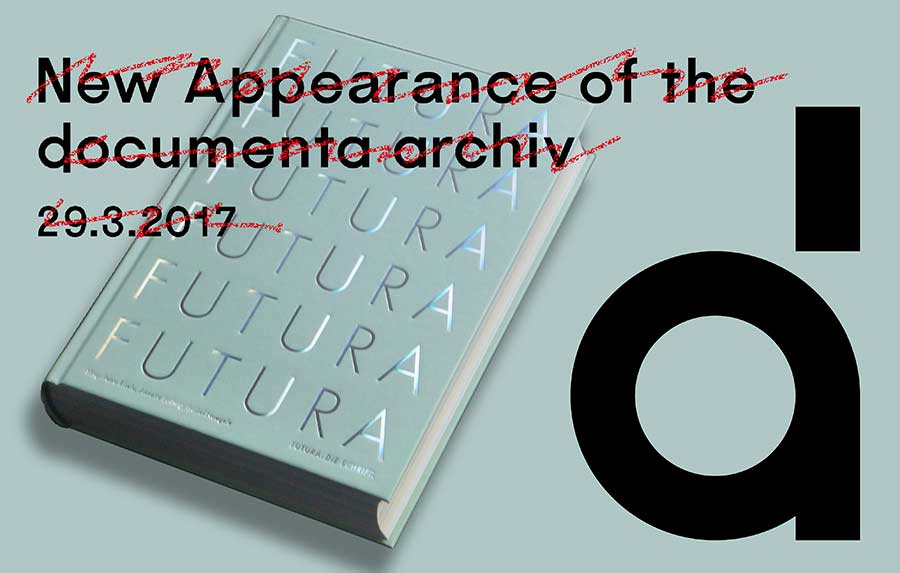
Die Vorstellung eines neuen Buches, das sich ausschließlich der Schrift „Futura“ widmet, hatte Doc Baumann für den heutigen Termin schon länger geplant. Zufällig präsentierte das Kasseler documenta-Archiv drei Tage zuvor sein neues Logo und eine eigens entworfene Schrift. Ein passender Anlass, um auf gelungene und misslungene Beispiele geometrisch konstruierter Schriften einzugehen.
Wahrscheinlich versucht fast jeder Grafiker im Laufe seiner Ausbildung irgendwann einmal, eine eigene Schrift zu entwickeln. Da er oder sie bis dahin zumindest gelernt haben wird, dass die Konstruktion von Antiqua-Schriften mit Serifen eine recht anspruchsvolle Angelegenheit ist, wird das Vorhaben daher eher auf eine streng geometrisch konstruierte, serifenlose Linear-Antiqua hinauslaufen: Das o ein Kreis, das a ein Kreis mit einem kurzen Balken rechts daneben, das d einer mit längerem Balken und so weiter.
Menschen in der Ausbildung dürfen das. Spätestens, wenn sie mit geeigneter Software aus den strengen Zeichen einen Font basteln und Headline- oder – schlimmer noch – Fliesstext generieren, wird ihnen auffallen, dass das Ergebnis weder angenehm aussieht noch halbwegs lesbar ist. Das ist eine verzeihliche Jugendsünde, eine Übung, die über Versuch und Irrtum vielleicht irgendwann zu brauchbarer Typographie führen wird. Per aspera ad astra, hätte man früher gesagt.
Wesentlich bedenklicher ist es hingegen, wenn sich das Archiv der documenta eine derartige Schrift als Hausschrift entwerfen lässt – beziehungsweise das Ergebnis eines solchen Auftrages akzeptiert und fortan praktisch zu nutzen androht. Immerhin gilt die documenta weltweit als eine der wichtigsten periodischen Ausstellungen für zeitgenössische Kunst. Das Archiv, in dem alles rund um diese Ausstellungen seit 1955 gesammelt wird, sollte also auch im eigenen Erscheinungsbild Maßstäbe für gute Gestaltung setzen.
Das oben rechts abgebildete neue Logo dagegen ist durchaus gelungen. Es verwendet eine Kombination aus d (für documenta) und a (für Archiv). Allerdings würde dieses a viel besser zum Figurenbestand der Schrift passen als die aus der Reihe fallende und eher der Helvetica-Familie zugehörige Variante.
Futura – der lange Weg zu einer guten Schrift
Betrachtet man die ersten Entwürfe zu einer der (neben der Helvetica) einflussreichsten Schriften der Neuzeit, der Futura, so erinnert daran manches an die misslungenen Konstruktionen der Lettern des documenta-Archivs. Entworfen hat sie Paul Renner in den Zwanzigerjahren des vorigen Jahrhunderts.
Fachleute kennen diese Vorstufen zwar aus verschiedenen Publikationen – dass sich allerdings ein ganzes Buch mit über 500 Seiten ausschließlich mit dieser Schrift, ihrer Entwicklung, Verwendung und Bedeutung befasst, ist bemerkenswert.
Der von Petra Eisele, Annette Ludwig und Isabel Naegele herausgegebene und beim renommierten Hermann Schmidt Verlag erschienene Band „Futura, die Schrift“ zeigt in seinem Einstiegskapitel den schwierigen Weg vom Konzept einer geometrisch aus Quadrat, Dreieck und Kreis konstruierten Typographie zu einer lesbaren Schrift, die auf ihre Betrachter zwar immer noch so – eben streng geometrisch und konstruiert – wirkt, die bei der mikrotypographischen Analyse ihrer Formen aber zeigt, dass sie zahlreiche Kompromisse eingehen musste, um diese Wirkung zu erzielen und dennoch ein gleichmäßiges Schriftbild zu gewährleisten. Von der Einlösung dieses Anspruchs ist die Schrift des documenta-Archivs nicht nur viele Punkt und Cicero, sondern meilenweit entfernt.
Abenteuerliche Buchstabenformen
Auch die Futura hat einmal mit zum Teil abenteuerlichen Buchstabenformen begonnen. So lassen sich frühe Formen von a, g, m, n, und r bestenfalls phantasievoll bezeichnen. Heutige Betrachter wird irritieren, dass auch das inzwischen völlig vergessene Lang-s als Variante auftaucht.
Die Schrift des documenta-Archivs weist ebensolche Typo-Monsterchen auf, etwa das fast zum Kreis geschlossene kleine e, das eher aussieht wie ein griechisches Theta. Die Buchstaben d und p sind nicht weniger seltsam, und von einigen Ziffern schweigt man am besten ganz. Die Tugend des Typographen besteht darin, den gesetzten Text auf seinen Inhalt hin durchsichtig werden zu lassen; nur im Ausnahmefall darf sich eine Schrift als wahrgenommene Form ins Bewusstsein ihrer Betrachter drängen. Eigenwillige Entwerfer und ihre Schriften missachten diese Regel. Die Buchstaben machen auf sich selbst aufmerksam und behindern so aktiv die Kenntnisnahme des Textinhalts.
Wenn Sie an Typographie interessiert sind, darf ich Ihnen dieses „Futura“-Buch ans Herz legen. (Hermann Schmidt Verlag, Mainz 2017, 520 Seiten, 50 Euro). Es lässt Sie den Weg einer Schrift von ihren frühsten Anfängen bis hin zu ihrer internationalen Karriere mit etlichen Textbeiträgen und zahllosen Abbildungen und Satzbeispielen nachverfolgen. Eine Schrift, in ihrer reifen Form sozusagen bis aufs Skelett abgemagert, so dass sich nichts mehr wegnehmen ließe, ohne dass die Erkennbarkeit in Frage gestellt würde – und dennoch (oder eben deswegen) ein Klassiker, der auch nach fast einem Jahrhundert nichts von seinem „modernen“ Reiz verloren und weiter seine Berechtigung im Schrifteinsatz hat. Paul Renner hätte es gewiss gefreut, dass seine Futura auch in jener zitierten Zukunft, die heute unsere Gegenwart ist, nicht vergessen ist.
Die Schrift des documenta-Archivs ist m.E. eine typographische Mißgeburt. Ich habe selten ein mißlungeneres Schriftbild gesehen. Ich frage mich nur, welche documenta-Verantwortlichen diese
total vermurkste Schrift für das „Archiv der documenta“ ausgewählt haben. Fachleute auf künstlerischem bzw. graphischem Gebiet können es wohl nicht sein. Beschämend.